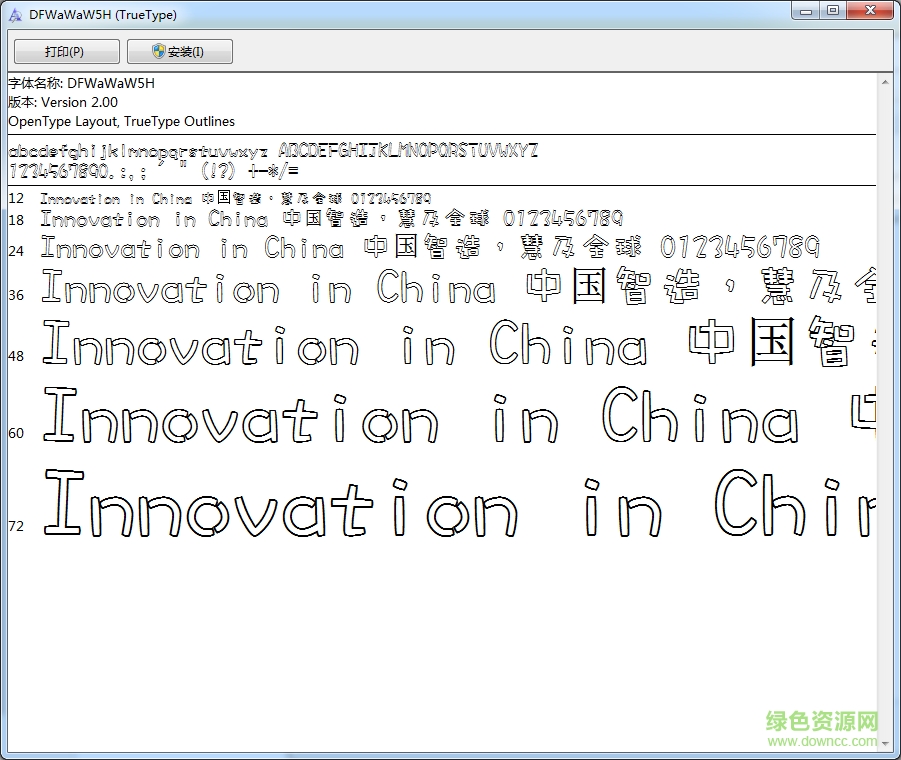
華康娃娃空心體w5是一款空心的華康字體軟件,字體以空心顯示獨具個性,支持中文英文漢子互相轉(zhuǎn)換輸入使用非常便捷??靵砭G色資源網(wǎng)下載體驗吧!
華康娃娃空心體w5是一款應(yīng)用于廣告創(chuàng)意設(shè)計方面的繁體中文字體,該字體每一個字都是空心效果,但整體排版十分出色,并且字庫完整,可以適用于名片設(shè)計、平面設(shè)計、廣告設(shè)計、報紙雜志、企業(yè)LOGO、商標(biāo)注冊、電視臺廣告等領(lǐng)域,有喜歡的網(wǎng)友可免費下載收藏。
可愛風(fēng)格設(shè)計的手寫字體,它能夠為用戶提供中英文雙語字體,娃娃體雖然不夠端正,但是別具童真氣息,非常受用戶的喜歡,本款中文為繁體字。